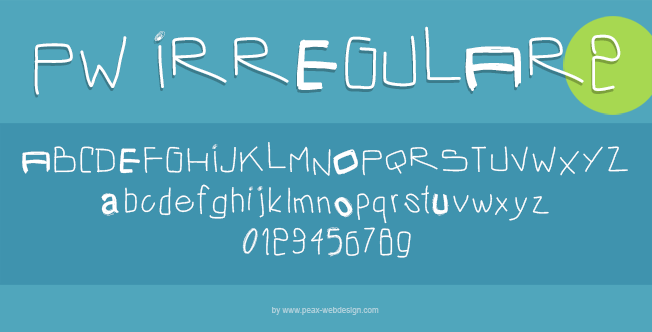
PW Irregular two, police manuscrite .ttf
Dans la série des ppolices de caractères irrégulières, en voici une nouvelle qui fait suite à PW Irregular sortie le mois dernier. La similitude réside dans les graisses différentes sur certains caractères, mais cette nouvelle typo diffère par son aspect rectangulaire. Son graphisme la rend lisible à toutes les tailles, il y a donc de quoi se faire plaisir et laisser vagabonder son imagination pour des titres et posters créatifs !